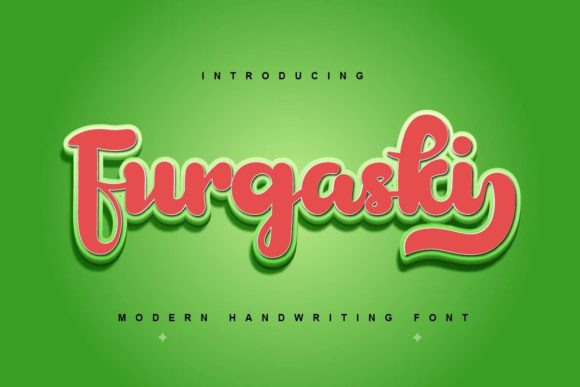
Creativefabrica Furgaski Font 2021
[Creativefabrica] Furgaski Font (2021)
Furgaski - это красиво изогнутый рукописный шрифт с привлекательным стилем и мягким, оригинальным штрихом.
Этот великолепный шрифт будет выделяться при включении в ваши проекты.